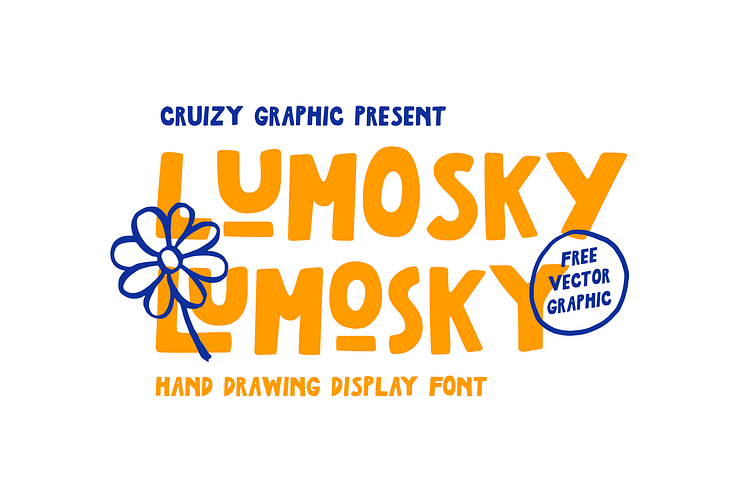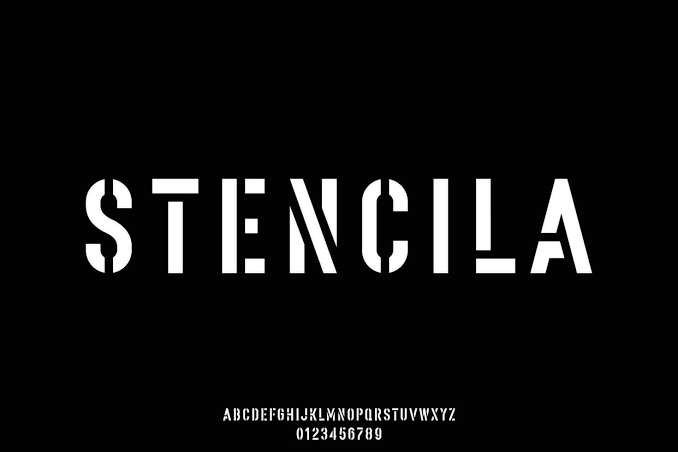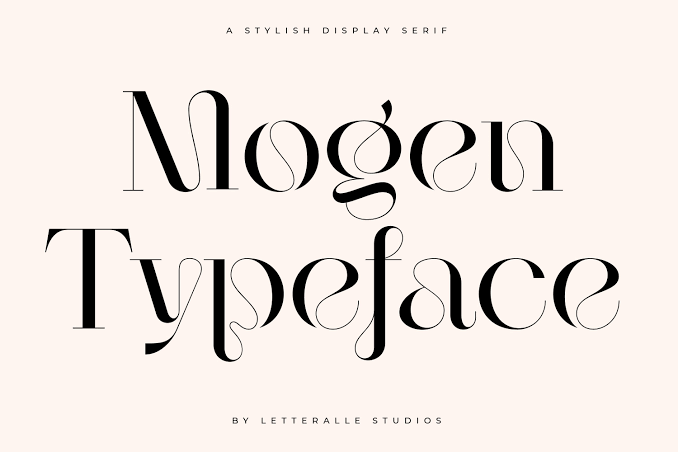
Font display dibuat dengan unik dan cukup nyentrik karena terkadang memiliki dekorasi menarik efektif membuat desain tampil mencolok. Display font yang unik dibuat untuk digunakan pada ukuran yang besar karena bentuk unik akan sulit dibaca pada kuran kecil. Dalam desain memilih font display biasanya karena beberapa alasan seperti tampilan font yang menarik perhatian, unik dan rumit.
Font yang didesain untuk digunakan pada ukuran teks yang besar, maka font ini akan banyak digunakan sebagai headline pada desain. Terkadang juga digunakan untuk kebutuhan signage bergantung style font display yang digunakan. Untuk menggunakannya dalam desain perhatikan kebutuhan dan kelebihan dari font display, sehingga tidak salah memilih.
6 ALASAN MEMILIH FONT DISPLAY
Penggunaan gaya font tertentu dalam sebuah desain mempertimbangkan beberapa hal tema desain, pesan dan tujuan agar font relevan. Desain akan tampil menarik jika bisa memilih gaya display yang tempat. Biasanya penggunaan font display mempertimbangkan beberapa alasan berikut ini sebelum memilih untuk desain:
Gaya Font yang Unik
Alasan utama menggunakan font display adalah karena gaya hurufnya yang unik dan tampil beda dari yang lain. Bentuk huruf pada font ini tidak sesederhana font serif atau sans serif. Terkadang font display akan memiliki gaya unik seperti penggunaan gaya inline atau outline, huruf yang bergelombang, atau dekorasi-dekorasi unik lainnya.
Desain yang menggunakan font unik akan efektif menarik perhatian mata audiens daripada menggunakan font bersih yang sederhana. Gaya font display bisanya tidak sederhana, bergantung tema dan jenis fontnya. Dekorasi yang menarik akan meningkatkan keunikan pada berbagai jenis desain termasuk logo atau iklan.
Memudahkan Menarik Perhatian
Penggunaan font yang unik akan efektif meningkatkan daya tarik visual desain grafis. Font display sering digunakan untuk jenis teks desain yang besar sehingga mudah menarik perhatian. Untuk menarik perhatian display banyak ditemui pada jenis desain poster.
Bentuk font yang unik dan tambahan dekorasi tertentu membuat font efektif memikat perhatian. Gaya font bersih dan sederhana bisa tampil membosankan sehingga font display bisa menjadi pilihan menarik.
Membuat Headline, Judul dan Desain Iklan Menarik
Font display yang unik banyak digunakan untuk kebutuhan teks berukuran besar seperti headline dan judul. Dalam membangun desain yang menarik, penting untuk memfokuskan pemilihan font unik pada headline. Headline akan memiliki ukuran besar sehingga font unik akan mudah menarik perhatian.
Untuk digunakan sebagai font judul biasanya ditemui dalam jenis desain iklan atau poster karena sesuai dengan tema dan tujuannya. Font display tidak disarankan untuk digunakan pada teks dan desain yang berukuran kecil. Pada teks judul dan headline meskipun font display cenderung unik tetapi akan lebih mudah terbaca karena berukuran besar.
Dapat Digunakan untuk Berbagai Desain dan Tema
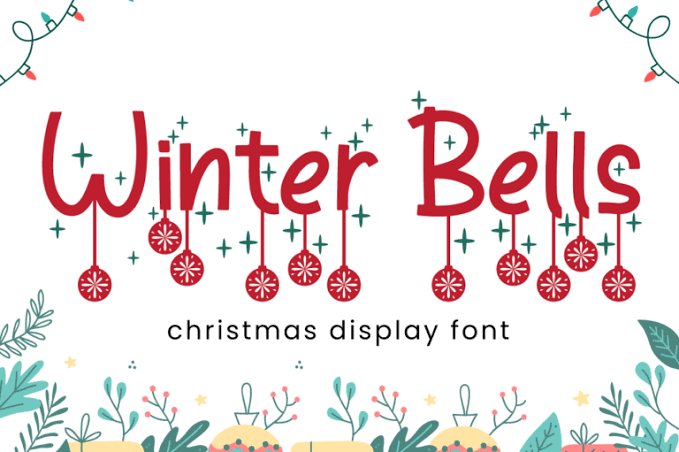
Alasan lain dalam memilih font display untuk digunakan dalam desain grafis karena mampu beradaptasi untuk berbagai tema. Style dari font display yang beragam membuatnya memiliki banyak pilihan menarik untuk digunakan dalam berbagai tema desain. Ada banyak style font display yang bisa mencerminkan berbagai tema seperti musim atau tujuan desain.
Font display juga bisa digunakan untuk kebutuhan berbagai jenis desain termasuk desain logo, kemasan hingga desain iklan. Setiap jenis desain akan menggunakan style font display yang sesuai tema desain. Misalnya desain poster natal menggunakan font display dengan dekorasi ikon natal.
Membuat Desain Lebih Ekspresif
Font display juga kerap dipilih karena lebih ekspresif dibandingkan dengan font sederhana tanpa dekorasi. Dekorasi berupa gambar atau serif yang panjang akan membuat font display bisa mengekspresikan tema atau pesan dengan lebih efektif. Misalnya font yang memiliki tekstur akan menciptakan kesan nostalgia retro, atau dekorasi pohon natal akan mencerminkan tema natal.
Garis huruf yang bergelombang pada font display akan efektif mengekspresikan kesan ramah dan menyenangkan. JIka desain grafis ingin lebih ekspresif terutama pada iklan dan desain poster bisa memilih font display yang unik. Pastikan dekorasi dan gaya huruf sesuai tema desain sehingga dapat mencerminkan pesan dan tujuan dengan baik.
VARIASI STYLE FONT DISPLAY
Font display dapat diciptakan dari gaya font lainnya seperti serif atau sans serif kemudian diberi dekorasi tambahan atau dibuat lebih unik. Misalnya jenis font display serif yang memiliki ukuran serif yang panjang dan unik sehingga tampil beda. Jenis-jenis font display bisa terlihat bentuk huruf dan dekorasinya.
Inlined
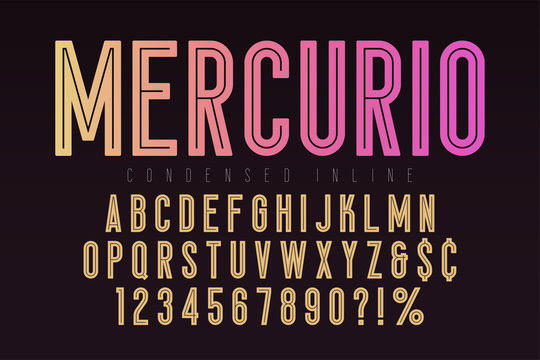
Gaya font dengan line tipis di dalam huruf menciptakan tampilan font yang unik dan beda dari yang lain. Style satu ini memiliki banyak line ada yang dibuat banyak ada yang tipis dan tebal. Agar line dalam font ini terlihat jelas penting untuk menggunakan font style ini pada judul dan headline.
Dalam memilih font display yang unik untuk digunakan dalam desain ada beberapa alasan yang bisa dijadikan pertimbangakan. Umumnya font display memiliki kemampuan untuk membuat desain tampil menarik perhatian dan unik karena gaya hurufnya yang unik. Font display memiliki banyak style typeface seperti inline, serif display, script display hingga hand drawn display. Setiap gaya font display bisa digunakan menyesuaikan kebutuhan dan tema desain, kebanyakan font ini digunakan untuk headline dan judul yang berukuran besar.